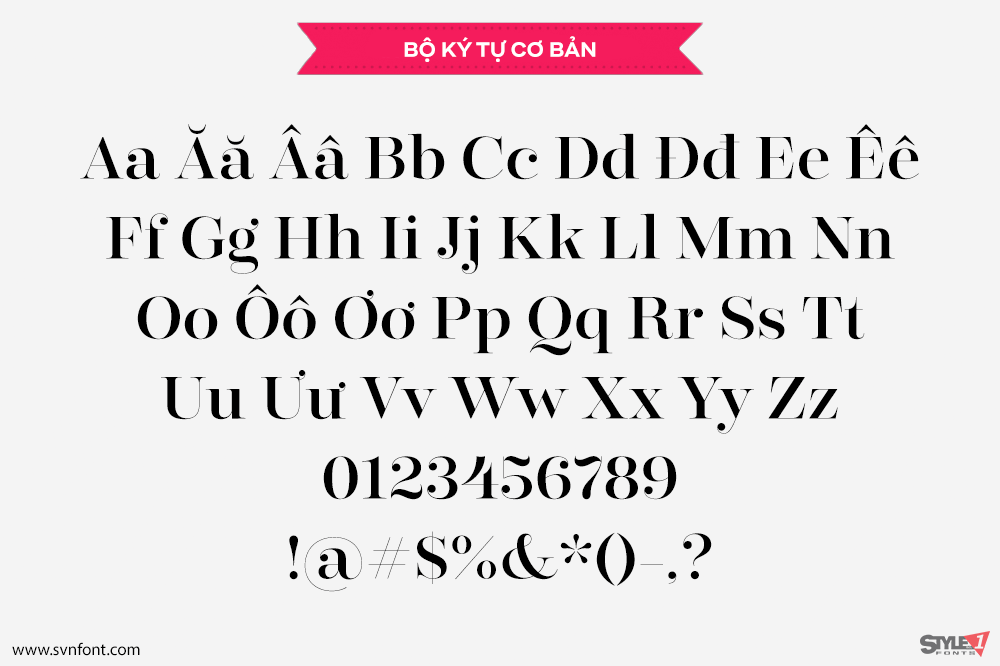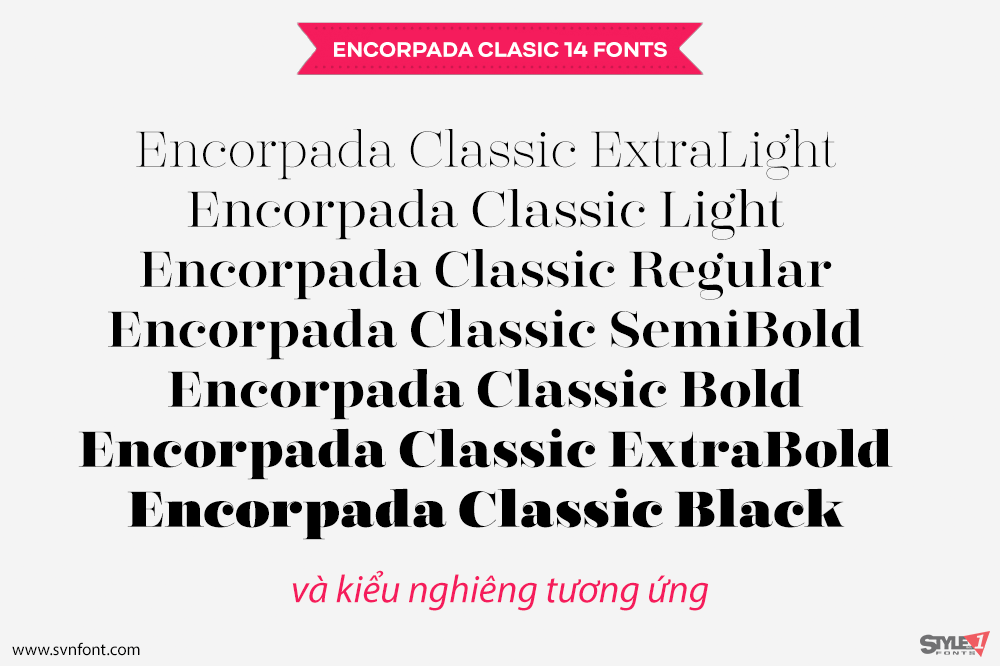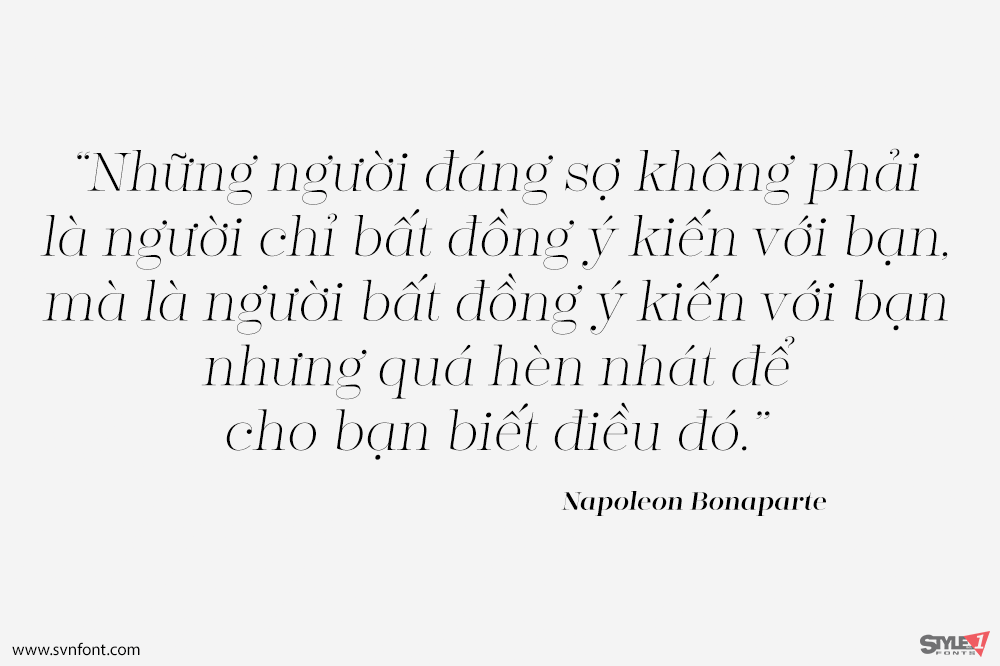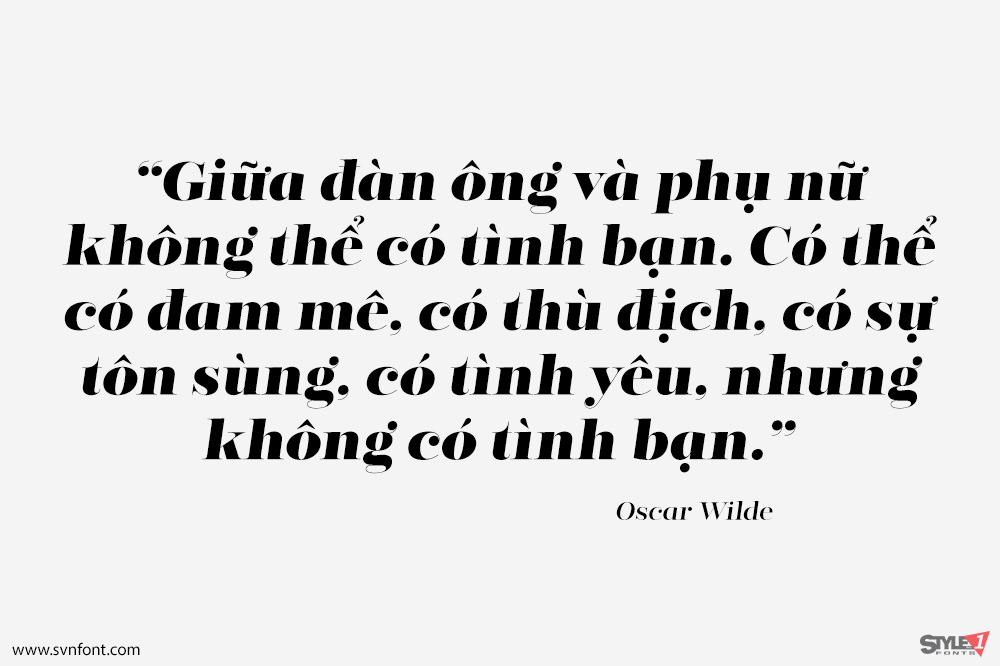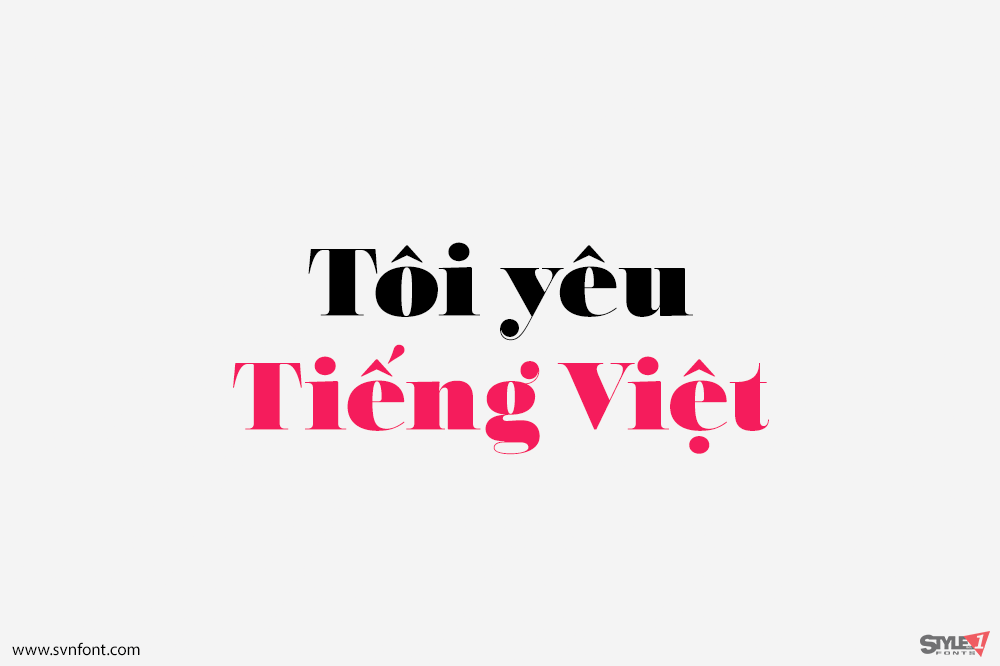
Encorpada Classic mang đến những đặc điểm tốt nhất của thể loại Didone, nhưng với diện mạo và cảm giác của thế kỷ 21. Với các chi tiết mượt mà, Encorpada Classic là một lựa chọn thanh lịch cho thư viện phông chữ của bạn. Bộ phông chữ Encorpada bắt đầu vào năm 2011 với sự ra mắt của Encorpada Black. Sau thành công ngay lập tức đó, vào năm 2012, dooType đã mang đến cho chúng ta Encorpada PRO. Encorpada Classic vẫn giữ vẻ ngoài và cảm giác chính của các phiên bản tiền nhiệm, nhưng được thiết kế với các cân nhắc chức năng hơn. Với 14 kiểu, Encorpada Classic là một lựa chọn tuyệt vời.
Nhà thiết kế: Eduilson Coan
Nhà phát hành: dooType